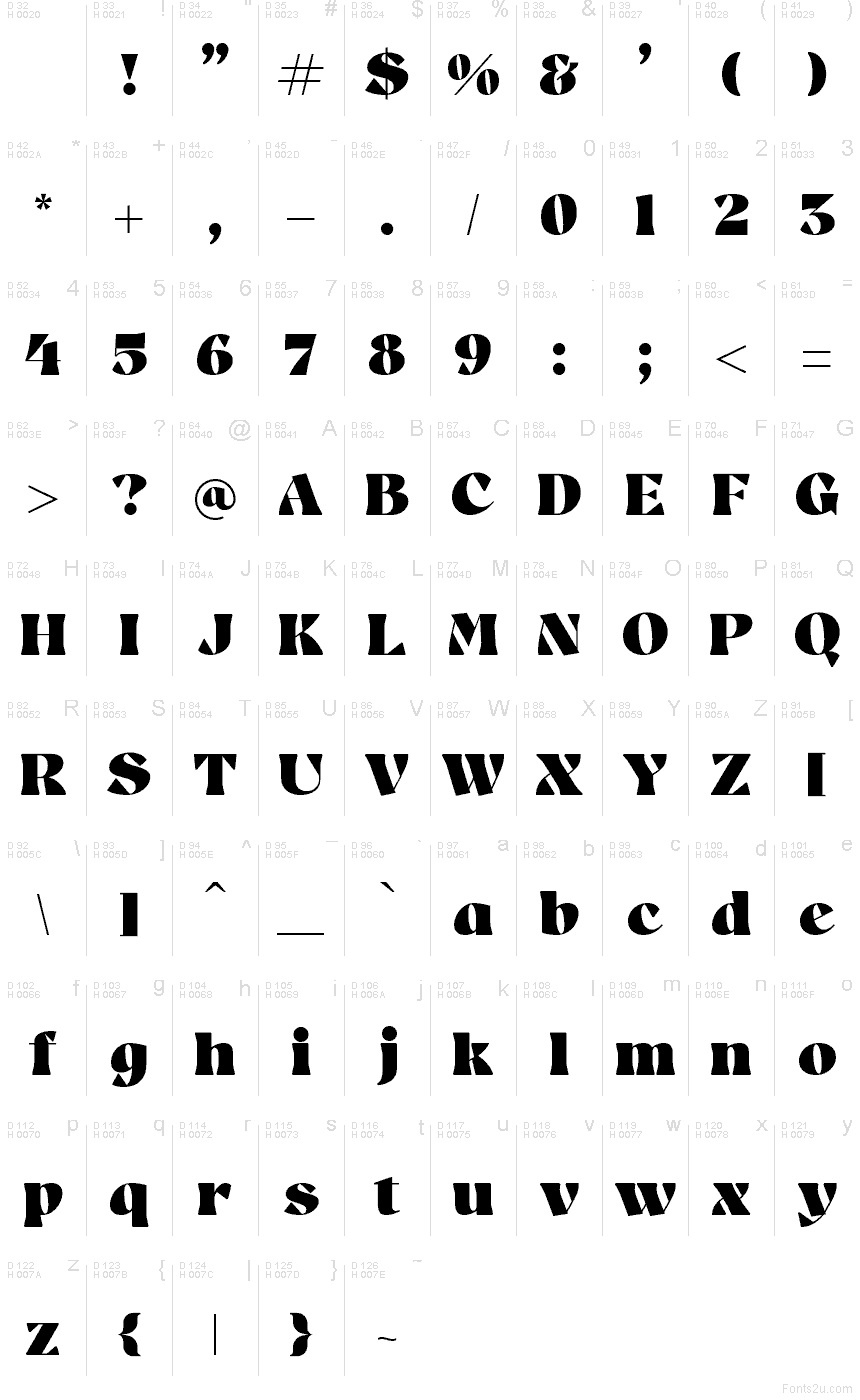
Milkstic Batter de TimelessType.co es una fuente display gratuita de estilo retro y groovy, con letras gruesas y dinámicas que parecen más moldeadas que dibujadas. Sus formas robustas, peso redondeado y cortes ligeramente irregulares le dan un aire pop suave de los años 70, mientras que su ritmo amplio la mantiene audaz sin resultar rígida.
Esta fuente gratuita encaja a la perfección en packaging, branding para cafeterías, titulares de pósteres, arte de álbumes y diseños juguetones para redes sociales, donde un toque cálido y nostálgico importa más que el acabado pulido. También funciona muy bien para títulos cortos y portadas, ya que las letras tienen suficiente personalidad y fuerza para sostenerse por sí mismas.